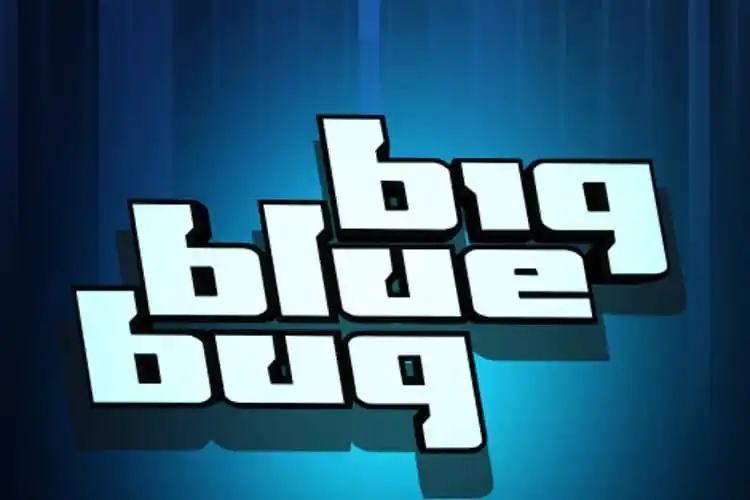
Aqui está uma descrição natural e envolvente para a página de download da fonte ‘Big Blue Bug Display Font’, conforme as especificações fornecidas: Na categoria de fonts display, encontramos ‘Big Blue Bug Display Font’. Esta font é perfeita para projetos criativos que exigem um toque de diversão. Com 18 versões diferentes – incluindo regular, itálico, esquadrão (super-ítalico), expansiva e estreita -, essa família de fonts oferece uma variedade incrível para atender a todas as suas necessidades. A font ‘Big Blue Bug’ é tão chamativa quanto seu nome sugere, com linhas robustas e detalhes vibrantes que deixam um impacto imediato. Essa font não apenas destaca seu texto, mas também transforma qualquer layout em uma cena de desenho animado. Se você está procurando por algo diferente para enfeitar suas aplicações digitais ou impressões, ‘Big Blue Bug’ é a escolha perfeita. Seu design único e vibrante certamente atrairá os olhos do seu público-alvo, tornando-o uma opção popular tanto em aplicativos móveis quanto em sites web.